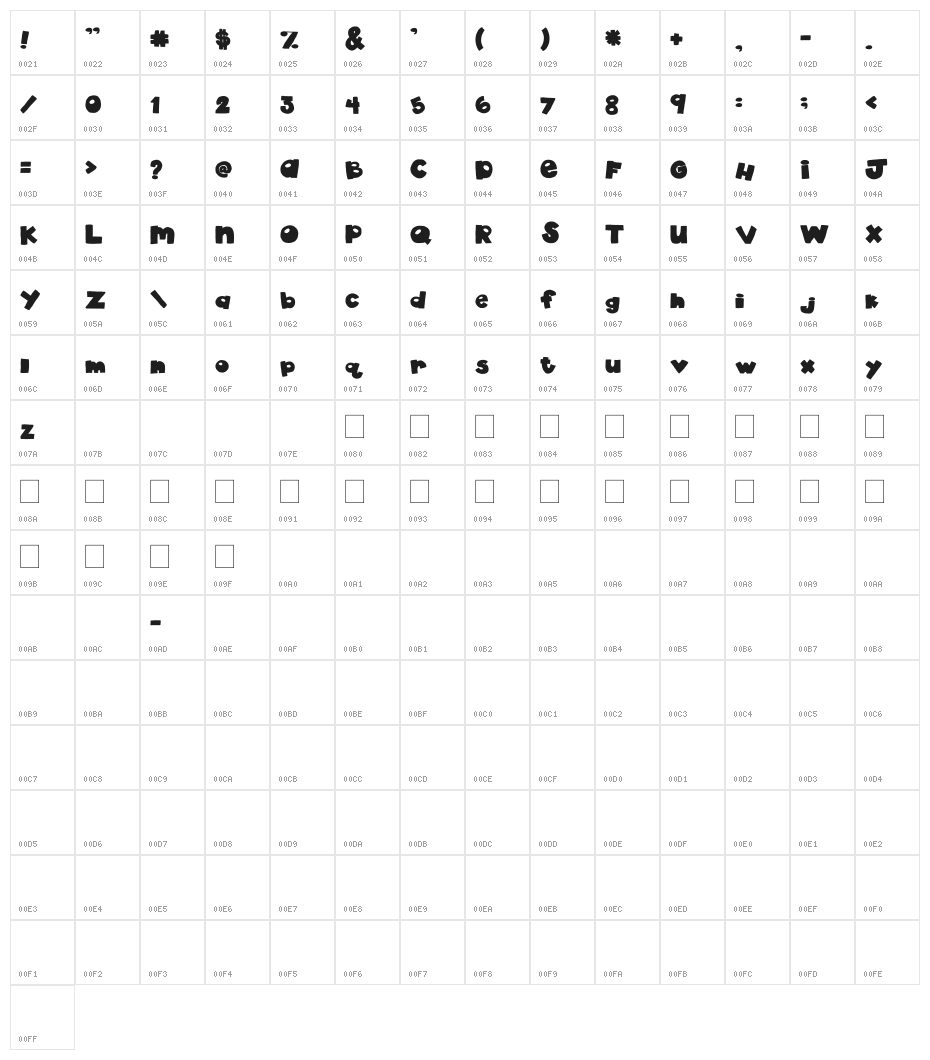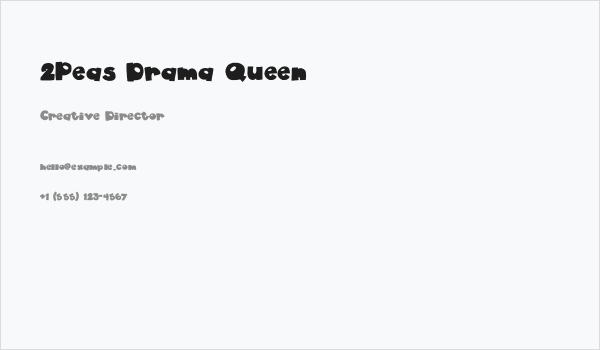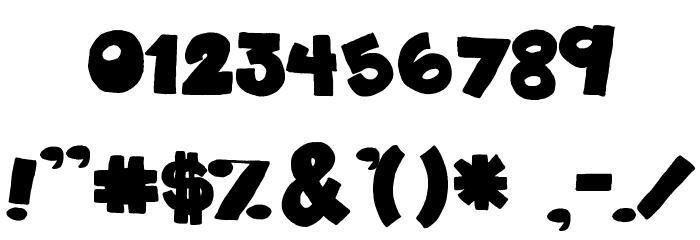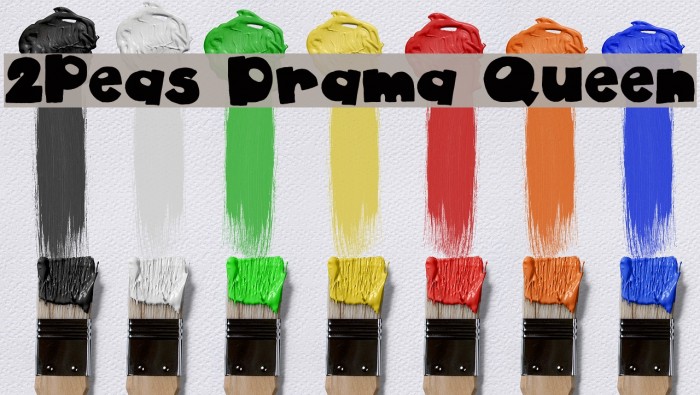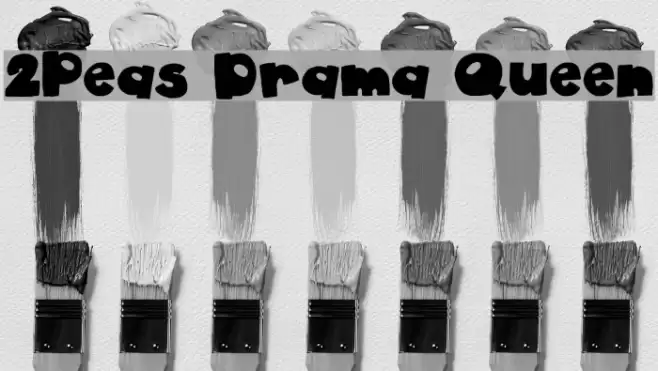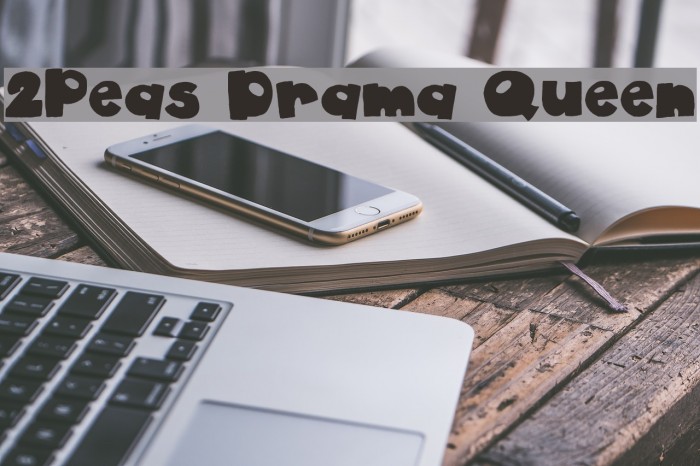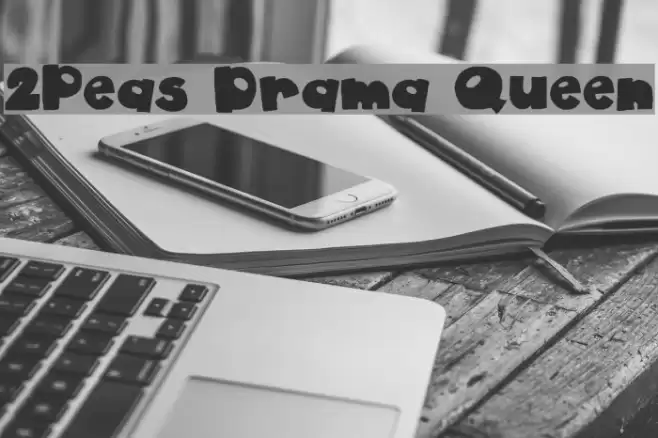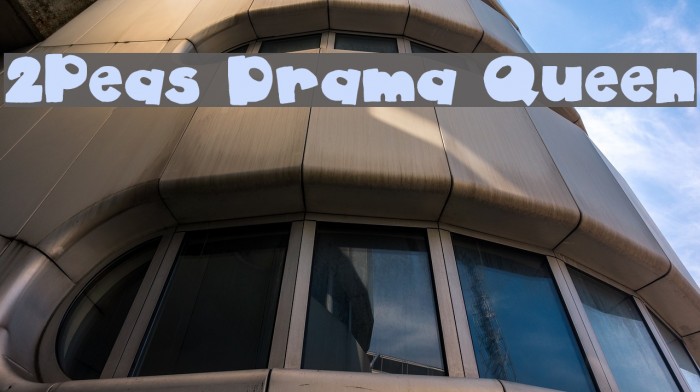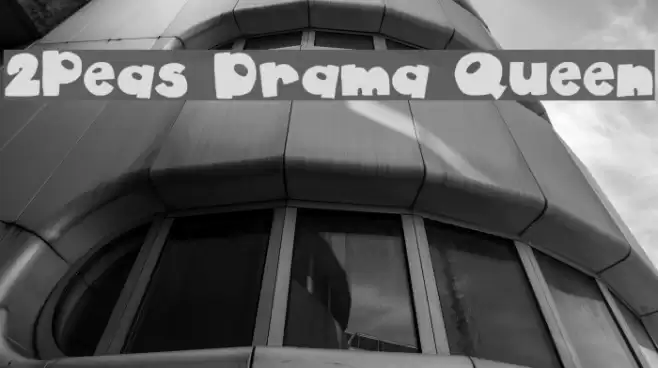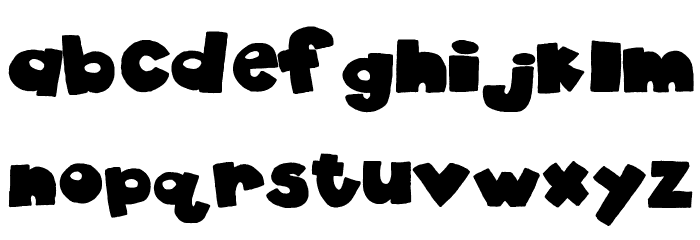
2Peas Drama Queen Font
| Stile generale | Playful, Whimsical |
| Caso d'uso | Headlines, Logos, Invitations |
| Progetti proposti | Ideal for children's books, party invitations, playful branding, and creative projects. |